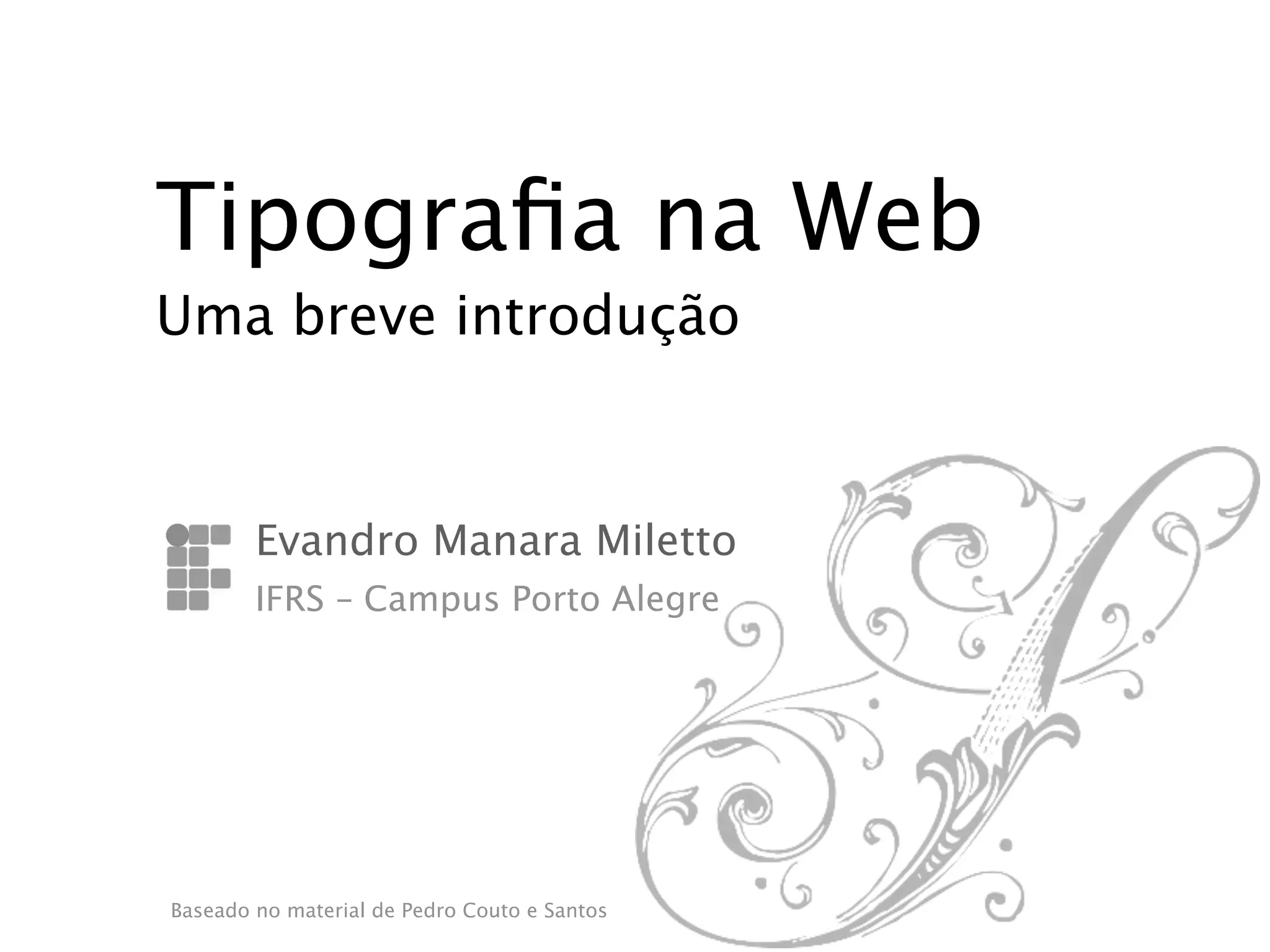
Tipografia na Web
Uma breve introdução
mundo sem tipografia?
conceito
A tipografia (do grego ‘typos’ —
"forma" — e ‘graphein’ — "escrita")
é a arte e o processo de criação na
composição de um texto, física ou
digitalmente.
O que significa
Tipografia trata da impressão dos
tipos.
Tipologia é o estudo da formação
dos tipos.
O termo tipo é o desenho de uma determinada família
de letras como por exemplo: verdana, futura, arial,
etc.
Objetivo da tipografia
Fazer com que o layout final tenha
uma “atmosfera” ou “ressonância”
apropriada ao conteúdo apresentado.
Alguns fatores que despertam o interesse visual
• escolha adequada de fontes tipográficas;
• composição (ou layout) de texto;
• sensibilidade para o tom do texto; e
• relação entre texto e os elementos gráficos na página.
Tipos de tipografia
Leitura contínua ou   Efêmera ou
Longa durabilidade    De impacto
-   Livros            -   Pôster
-   Jornais           -   Capas
-   Revistas          -   Logotipos
-   Manuais           -   Embalagens
-   Hipertexto        -   Anúncios
-   Sinalética
História
Classificação das fontes
4 grupos
básicos:
Elementos das fontes
Toda a fonte é composta por:
•   Linha de Base (baseline)
•   Linha Central (meanline ou midline)
•   Ascendente (ascender)
•   Descendente (descender)
•   Letra Caixa Alta (upper-case)
•   Letra Caixa-baixa (lower-case)
•   Altura de x (x-height)
•   Cabeça ou Ápice (apex)
•   Serifa (serif)
•   Barriga ou Pança (bowl)
•   Haste ou Fuste (stem)
•   Montante ou Trave (diagonal stroke)
•   Base ou Pé (foot)
•   Barra (bar)
•   Bojo (counter)
Anatomia das Letras
Times New Roman, 200 pt
Anatomia das Letras
Anatomia das letras
Braço                 Gancho
Barra
blTKQr     Haste
Bojo          Serifa           Perna
Cauda
Garamond, 200 pt.   Garamond, 200 pt
Anatomia das Letras
As letras são de três tipos consoante o seu desenho e tamanho
relativo:
Primeiro e terceiro exemplos: Stone Sans; segundo: Georgia.
Família de letras
Famílias de letras
As letras classificam-se de acordo com elementos gráficos
marcantes que as distinguem. Assim:
Famílias de letras
Alinhamentos
Justificado
todas   as   linhas   têm  o mesmo
comprimento e são alinhadas tanto a
esquerda quanto a direita.
Alinhado a direita
as linhas têm diferentes comprimentos e
são todas alinhadas á direita e irregulares
a esquerda.
Alinhado a esquerda
as linhas têm diferentes comprimentos e
são todas alinhadas á esquerda e
irregulares a direita.
Centralizada
as linhas têm tamanho desigual, com
ambos os lados irregulares.
Assimétrica
um arranjo
sem padrão previsível
na colocação das linhas
Arranjo dos tipos
seleção de fonte;
altura da letra (point size);
largura da linha;
espaçamento entre-letras (kerning),
espaçamento entre-linha (leading).
A finalidade é melhorar a legibilidade do texto a ser
escrito, facilitando o seu entendimento, além de
proporcionar conforto aos olhos do leitor
À largura de uma coluna de texto chama!se ‘medi
À largura de uma coluna de texto chama!se ‘med
Medida
As linhas criadas dentro da coluna ajudam o olho
seguir o texto e a sua largura deve ser combinada
o corpo de letra e a entrelinha de forma a facilita
olargura de uma coluna dede forma a facilita
corpo de letra e a entrelinha texto
Éviagem do olho de linha para linha.
viagem do olho de linha para linha.
As linhas criadas dentro    As armas e os Barões assinalados
da coluna ajudam o     As armas e os Barões assinalados
que da ocidental praia Lusitana,
olho a seguir o texto e a   que mares nunca dantesLusitana,
sua largura deve ser    por da ocidental praia
combinada com o corpo       por mares nunca dantes
navegados, passaram ainda além
de letra e a entrelinha   navegados, passaram ainda além
da Taprobana.
de forma a facilitar a   da Taprobana.
viagem do olho de linha
para linha.
Medida
oc osac euq sartel sartuo ed exiacne
.etnemacitpo ,sadatsafa odaisamed
Kern               Parte das letras que ‘sai’ do bloco
f fo fo
Permite o encaixe de outras letras que caso contrário
ficariam demasiado afastadas visualmente
Kern